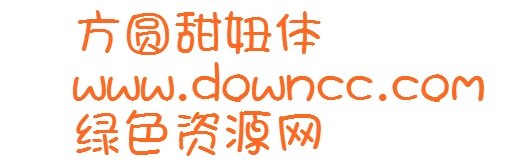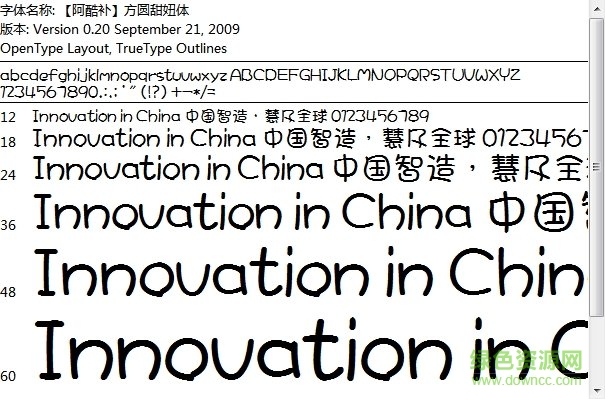
方圓甜妞體是阿酷補(bǔ)充完整的一款卡通字體,跟很多甜妞字體風(fēng)格類似,但在筆畫相連的部分做出了特色處理,讓圓潤和棱角結(jié)合,更加突出文字的可愛,綠色資源網(wǎng)誠意推薦!
方圓甜妞體字體是一款以卡通風(fēng)格的pop字體,字體俏皮可愛,趣味性十足,無多余的點(diǎn)綴圖案,讓文字更加突顯。
方圓甜妞體有著活潑圓潤的造型,字跡較為深沉,整體風(fēng)格十分出色,可以使用在兒童內(nèi)容的宣傳和藝術(shù)設(shè)計(jì)上。